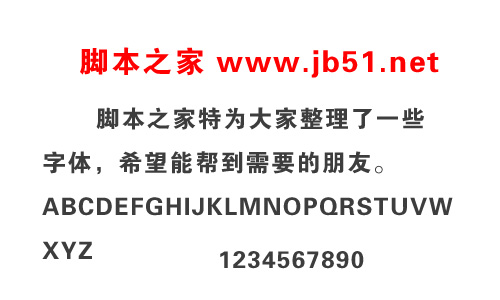
方正大黑_GBK字體是方正字體庫(kù)中的一種字體,方正大黑源自1971年上海字模一廠設(shè)計(jì)的行頭黑,字形結(jié)構(gòu)延續(xù)了鉛字時(shí)代的黑體風(fēng)格。這款字體的中宮緊湊,橫豎筆畫的兩端沒有喇叭口,豎和撇的起筆留有細(xì)微的飾角,筆畫粗壯有力。方正大黑的整體風(fēng)格中庸平和,具有明顯的時(shí)代特征,適用于報(bào)刊、雜志和書籍中的大型標(biāo)題。喜歡的朋友們可以前來下載使用。